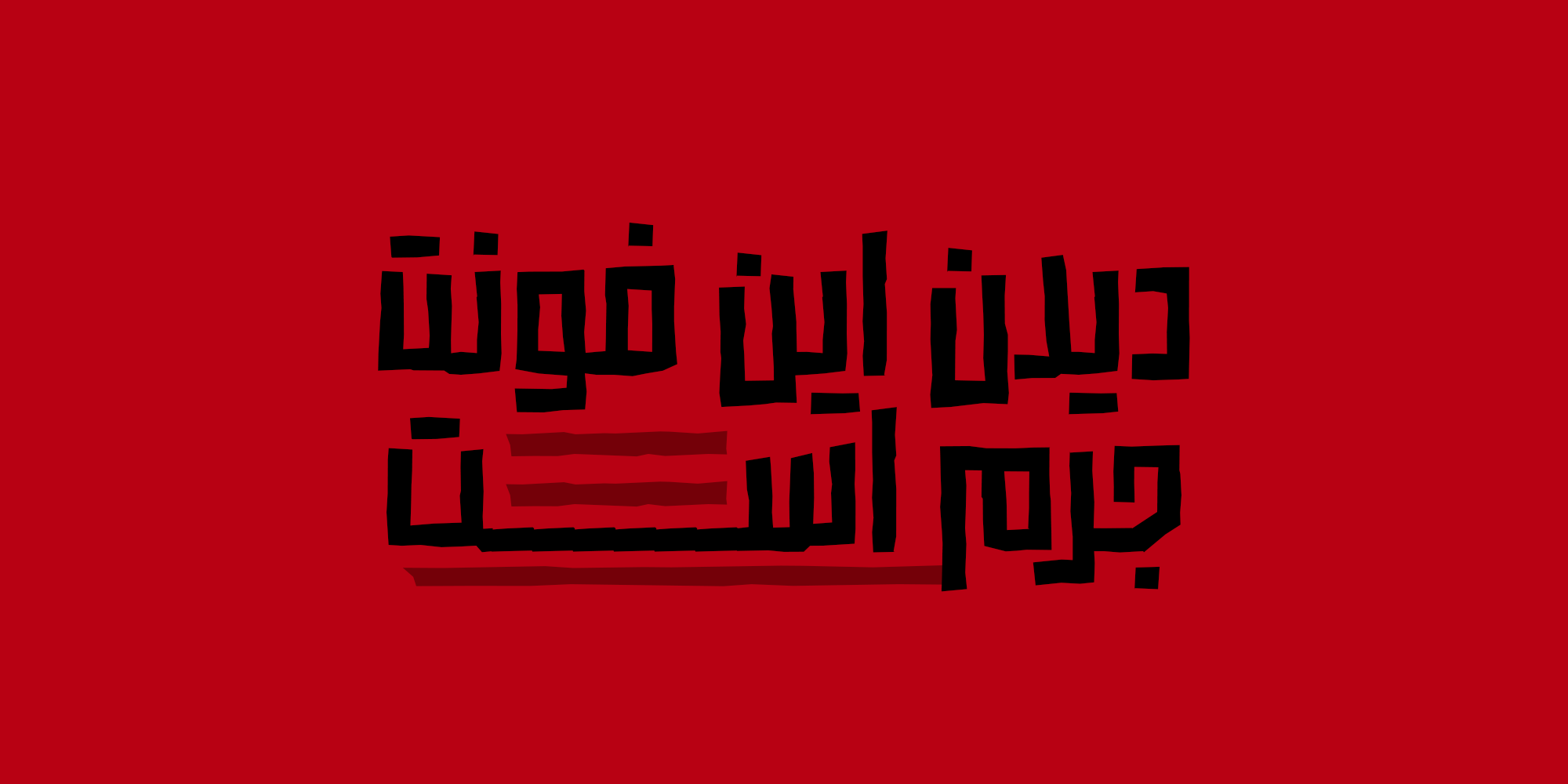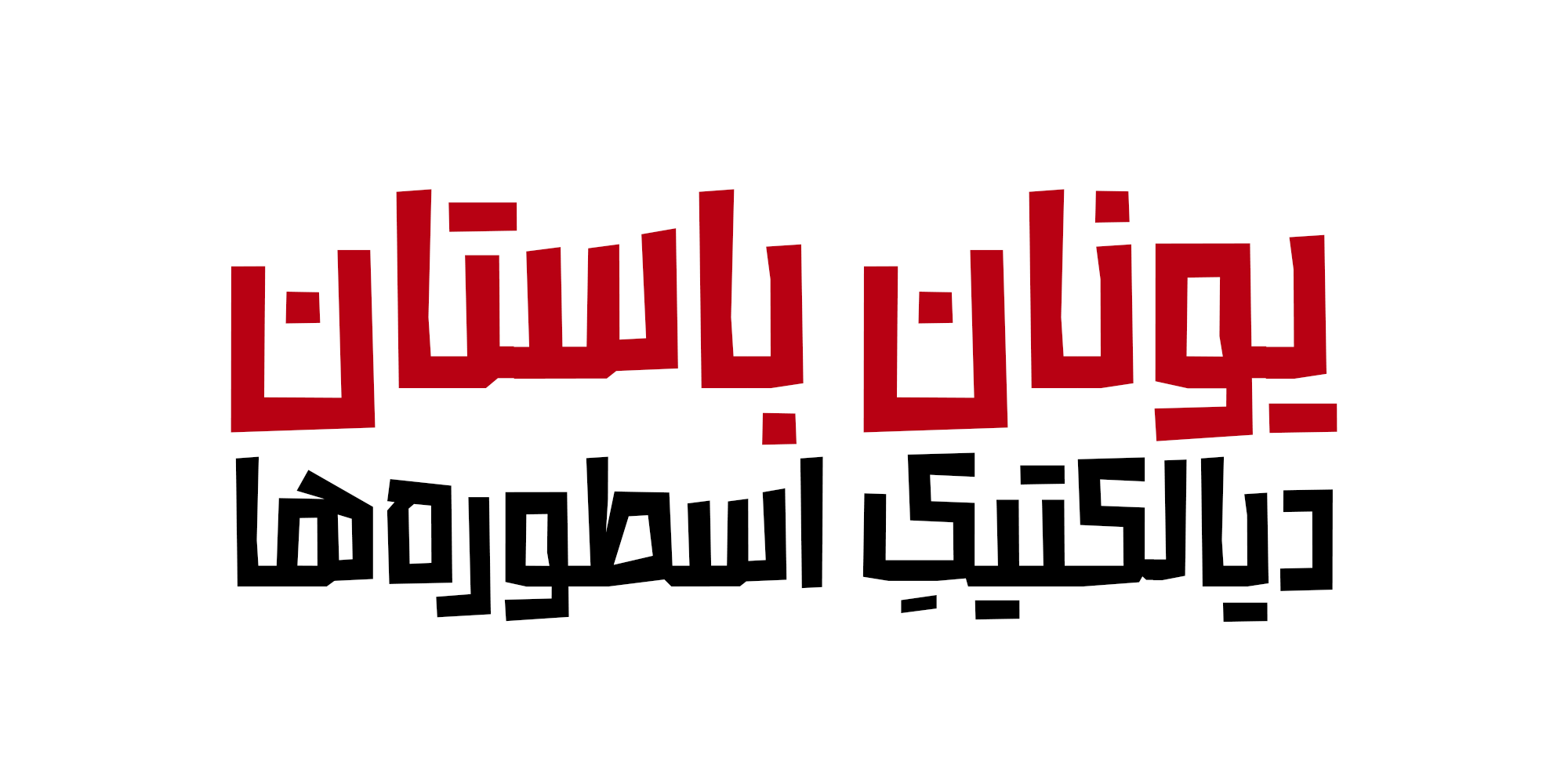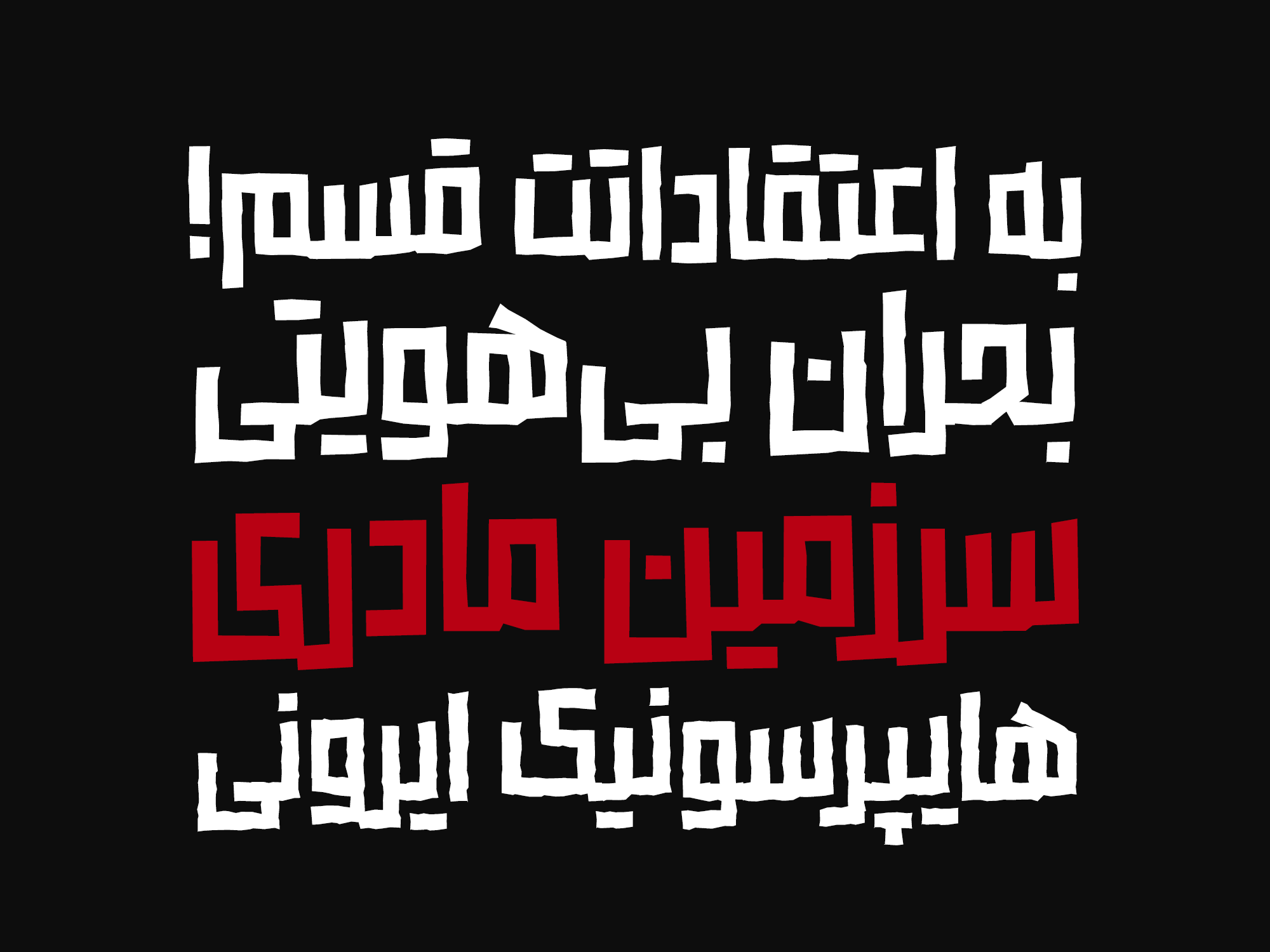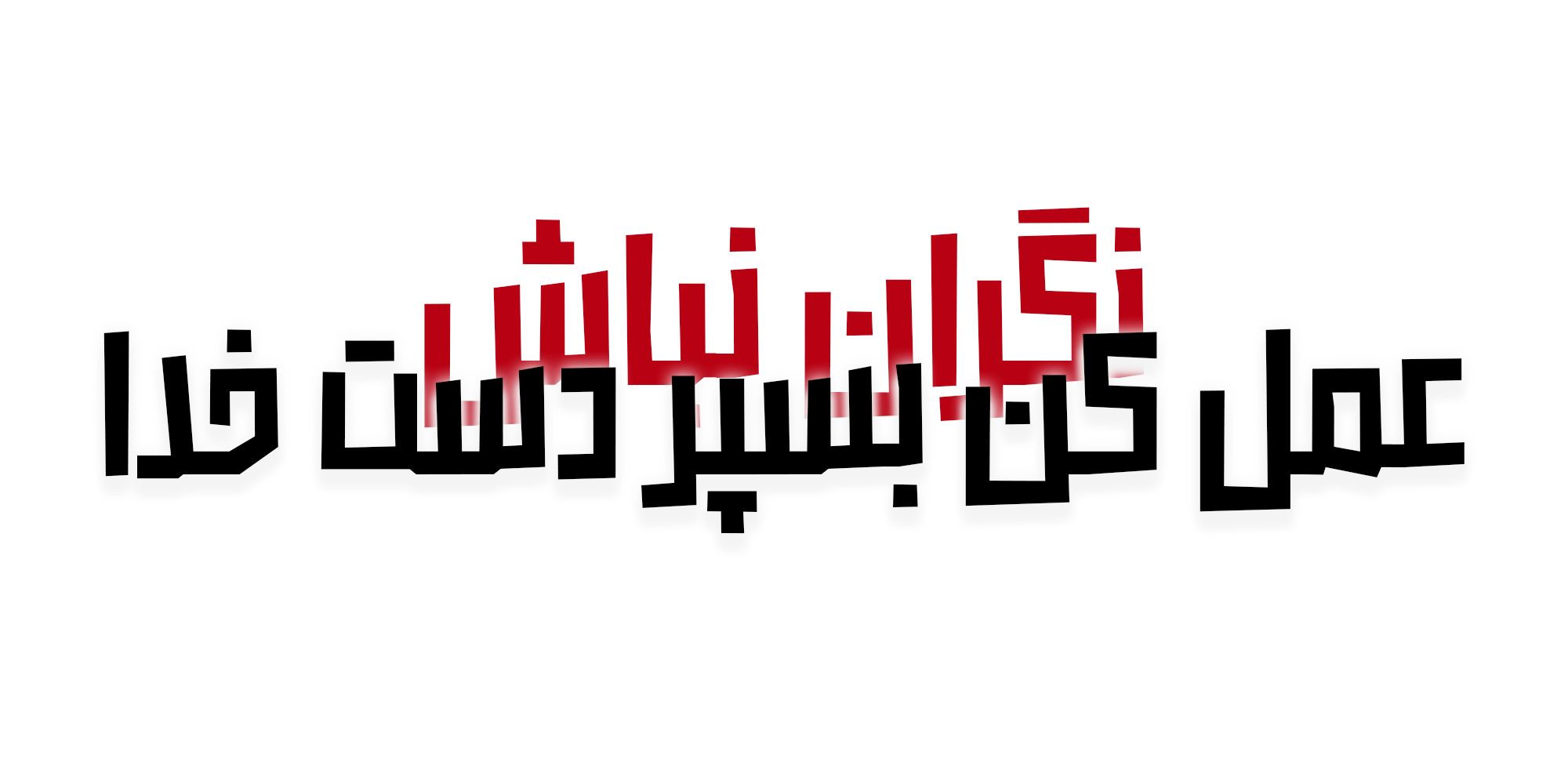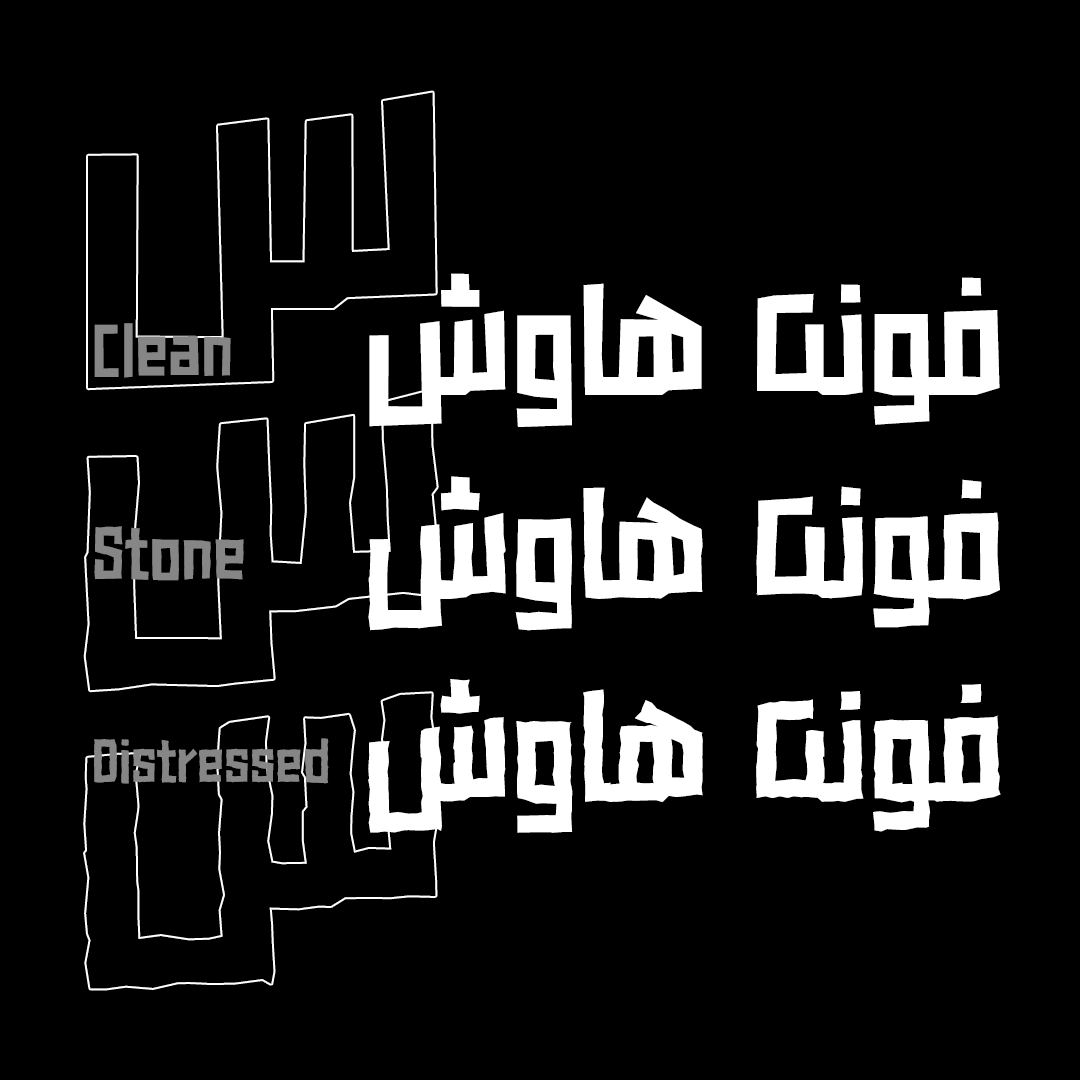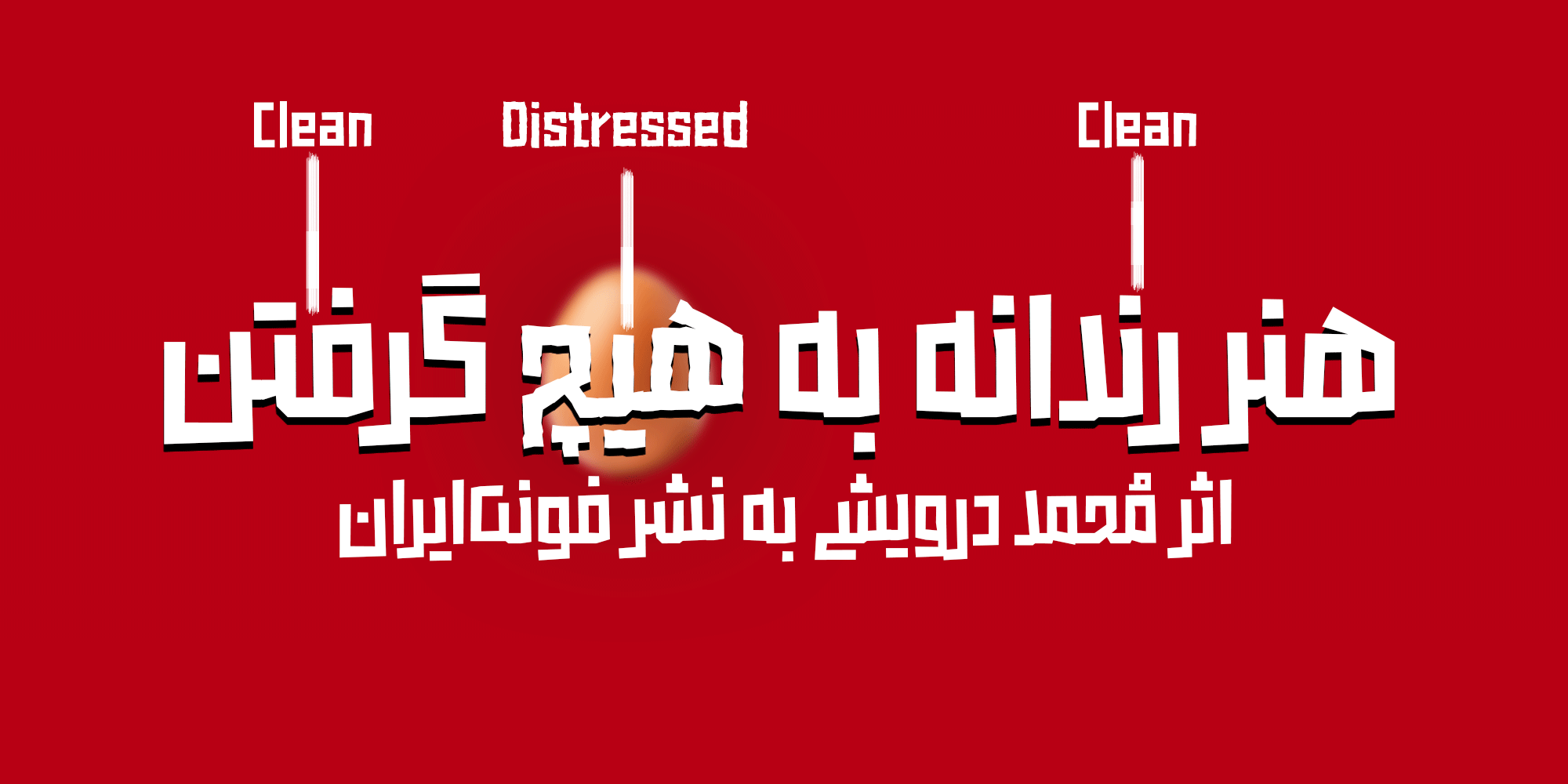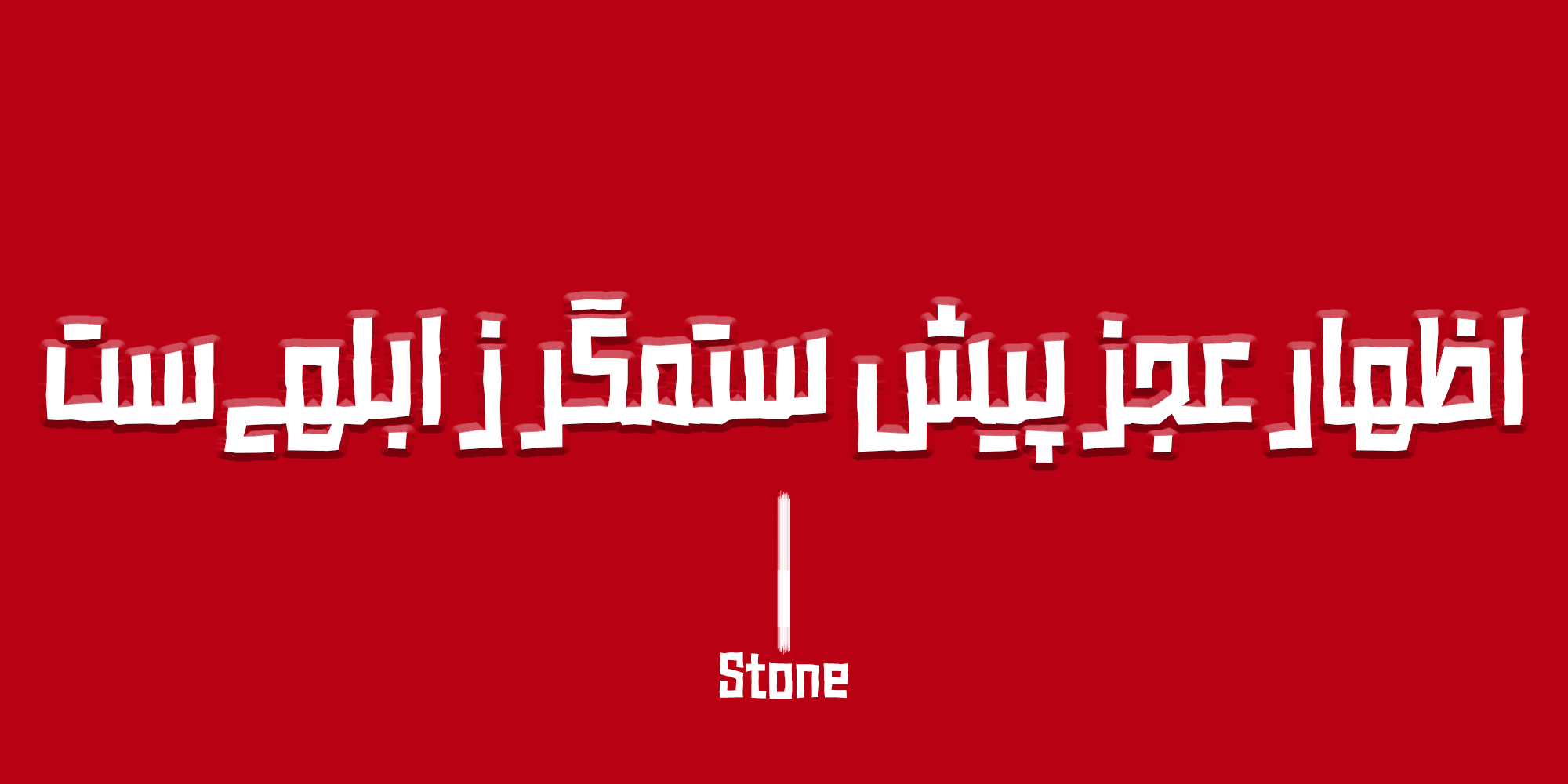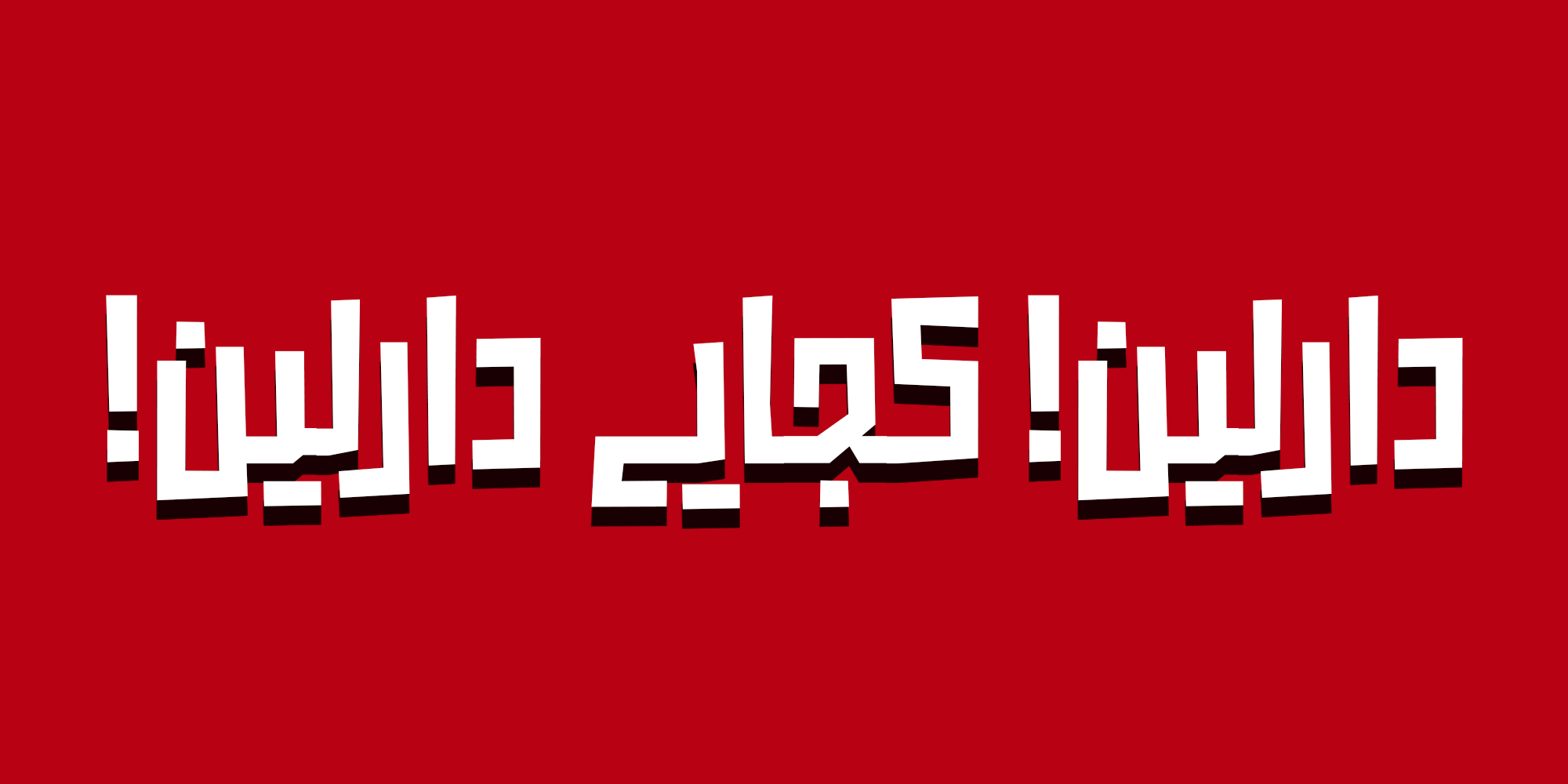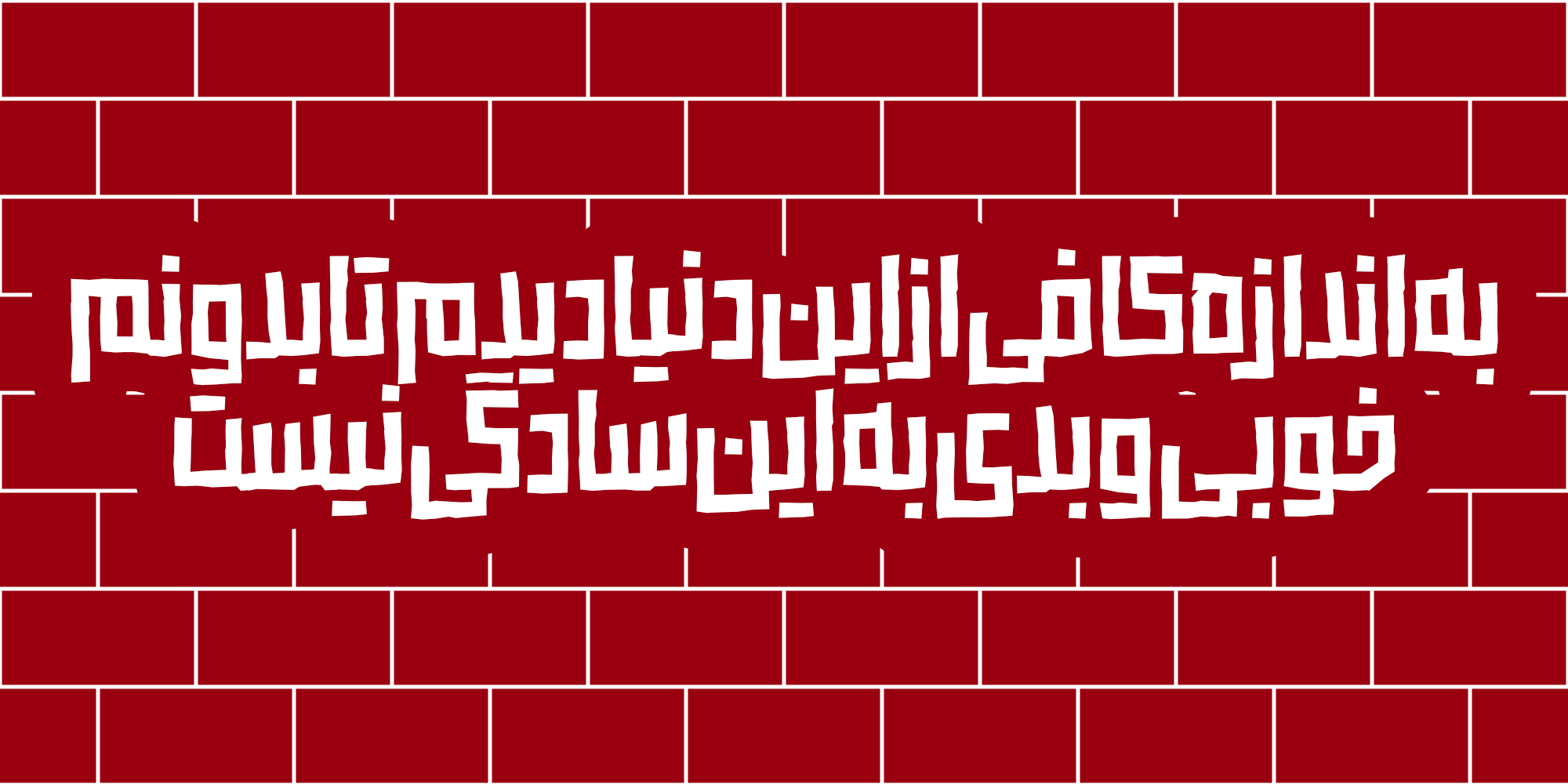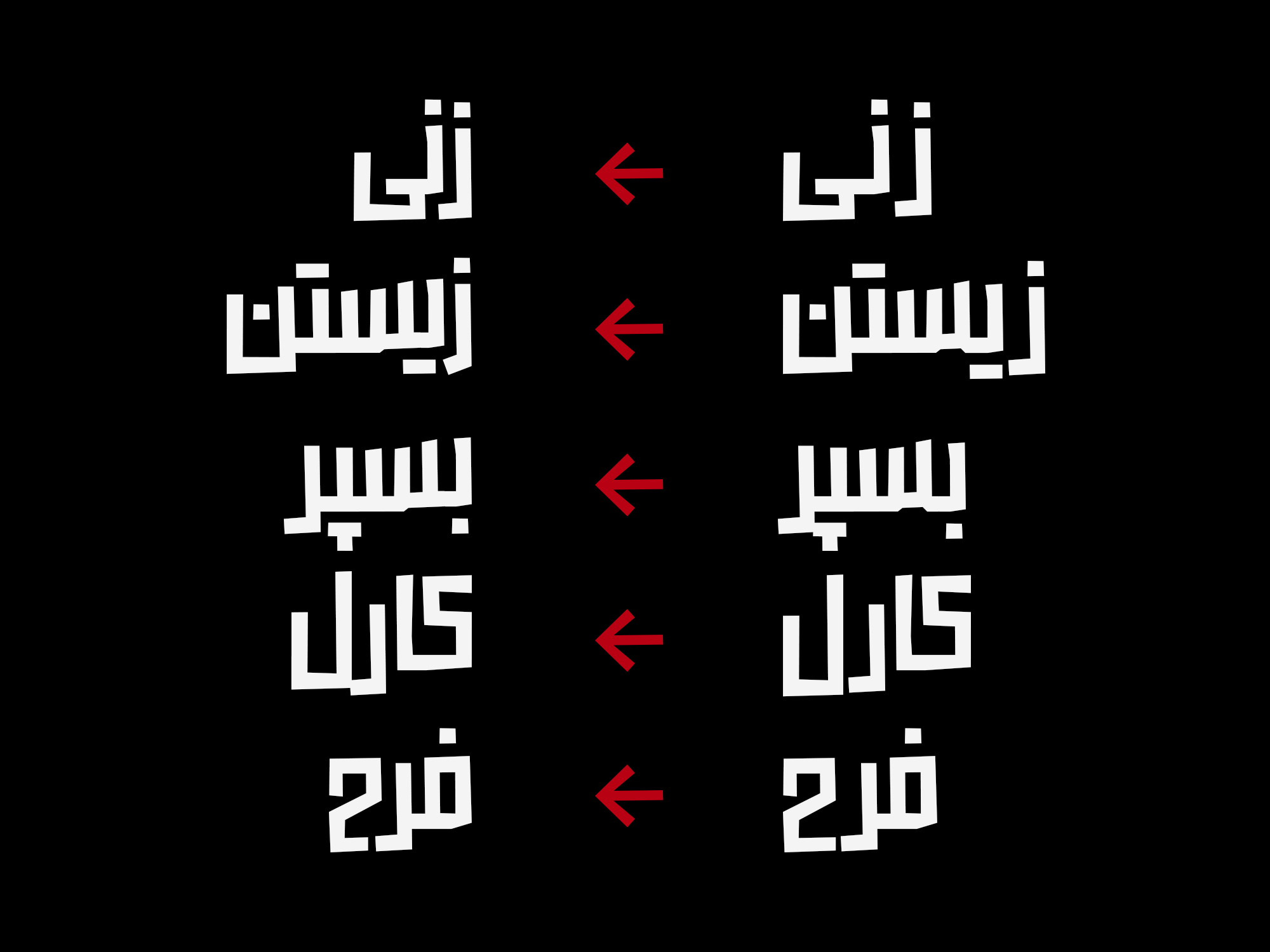
فونت هاوش دارای سه حالت است.
حروف جایگزین اجباری
فونت هاوش تمرکز زیادی بر حذف فضاهای منفی دارد. برای بسیاری از ترکیب های نوشتاری، جایگزین های شرطی در نظر گرفته شده است تا فضای منفی حذف شود.
تقریباً به اندازه تعداد گلیف های پایه، گلیف های جایگزین شرطی و اختیاری در فونت وجود دارد. به معنای دیگر، وجود جایگزین های شرطی و اختیاری، تعداد گلیف های فونت را به بیش از دو برابر میرساند.
فونت هاوش به طور خودکار از حروف ارتفاعساز برای ایجاد تنوع در نوشتار استفاده میکند.
جایگزین های اختیاری
برای ایجاد تنوع بیشتر در نوشتار، برای بسیاری از حروف و ترکیبها، حروف و ترکیبات جایگزین مشخص شدهاند که به زیبایی عنوان ها و تایپوگرافی نیز کمک میکند.
اِعرابگذاری کامل
پشتیبانی از علائم ارزی و ویژگی های اعداد همعرض و اعداد مخصوص UI
پشتیبانی از زبان های انگلیسی ، عربی، کردی و اردو
برای فونت هاوش به طور اختصاصی حروف انگلیسی هم طراحی شدند.
پشتیبانی از قابلیت های خاص حروف انگلیسی و حروف Small Capital